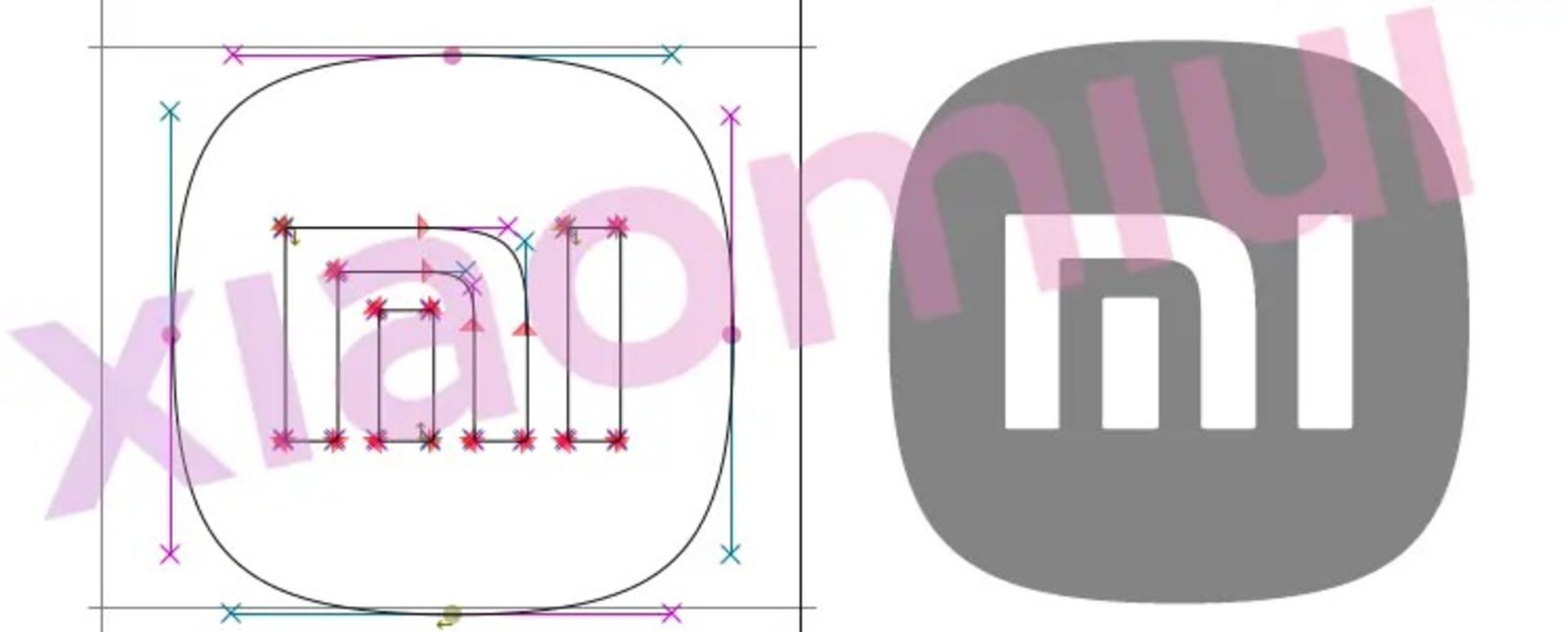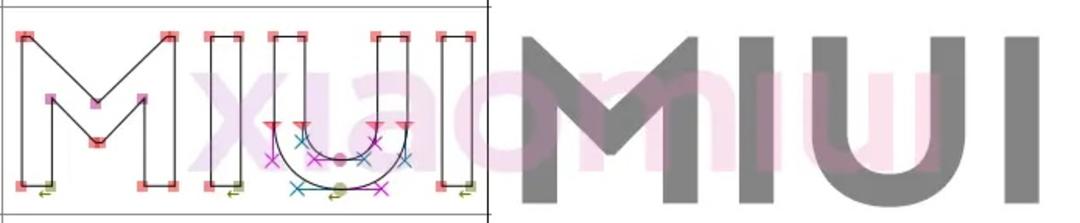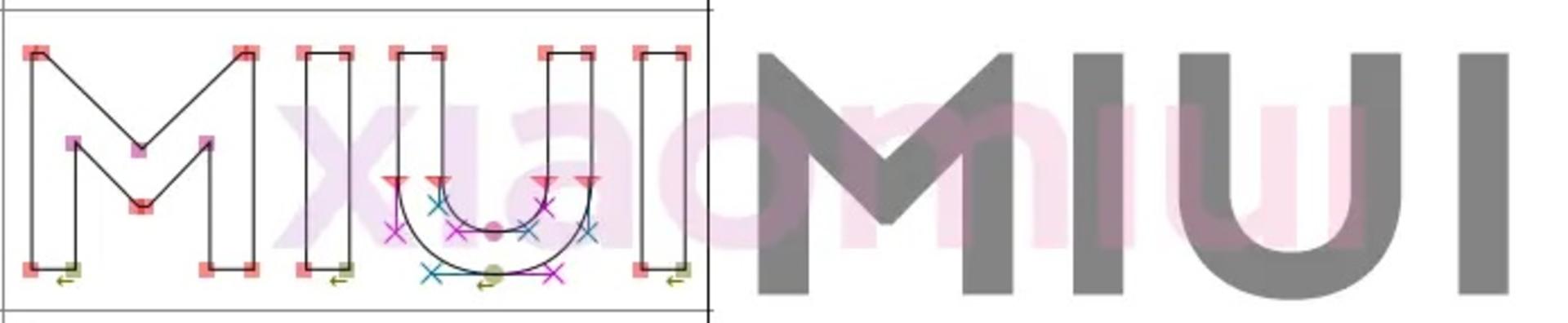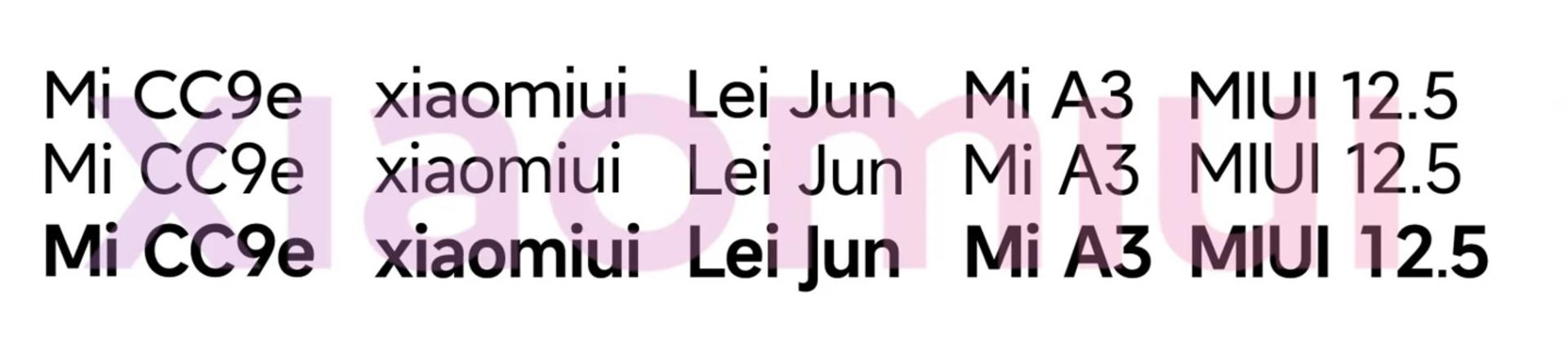
شیائومی بهروزرسانی سیستمعامل MIUI را برای گوشیهای هوشمند خود در فواصل زمانی منظم منتشر میکند و اکنون براساس گزارشی جدید از گیزموچاینا، این غول چینی در اواخر ماه دسامبر برای عرضهی MIUI 13 برپایهی سیستمعامل اندروید ۱۲ آماده میشود.
انتظار میرود MIUI جدید در تاریخ ۲۸ دسامبر (هفتم دیماه ۱۴۰۰) رسما معرفی شود؛ اما قبل از عرضه، افشای اطلاعات جدیدی نشان میدهد که شیائومی از فونت جدید Mi Sans و Mi Prototype 210317 در MIUI 13 استفاده خواهد کرد. فونتهای جدید جایگزین فونت Mi Lan Pro VF خواهند شد که درحالحاضر شیائومی از آن استفاده میکند.
بهنظر میرسد که فونتهای جدید در مقایسه با فونت فعلی، متونی گردتر با خطوط صافتر دارند که ظاهری مدرن به آن میبخشند. افزونبراین، مشخص شد که این فونت حاوی دو نشانهی خاص شامل لوگوی شیائومی و لوگوی MIUI است.
فونت جدید Mi Sans که شیائومی در MIUI 13 استفاده خواهد کرد با فونتهایی که در نسخهی فعلی موجود است، تفاوت دارد. فونتهای Mi Lan Pro VF از زمان انتشار MIUI 11 مورد استفاده قرار گرفتهاند و این شرکت باعرضهی MIUI 12.5، نام همان فونت را به Mi Sans تغییر داده است تا برای تحول بزرگ آینده آماده شود.